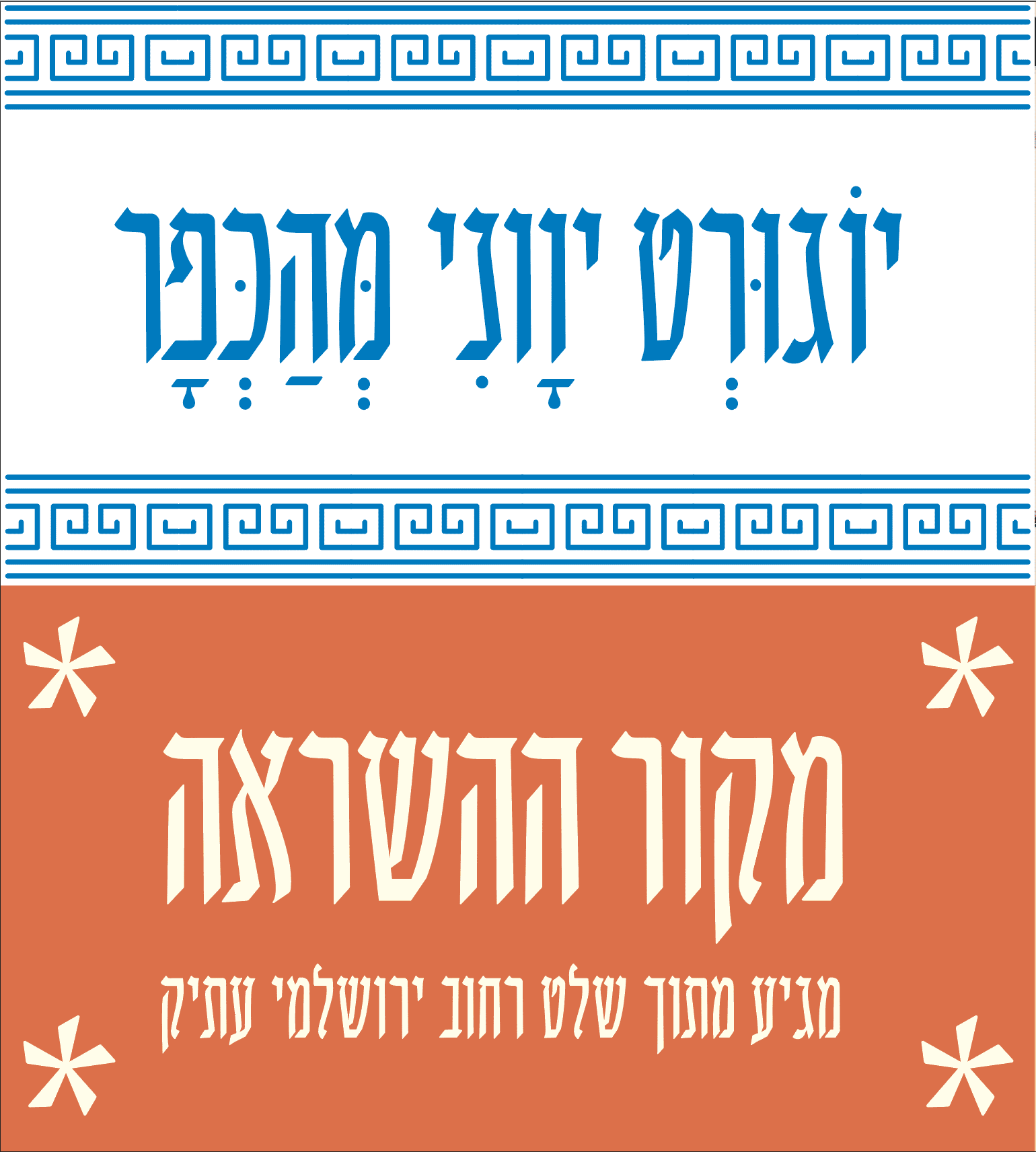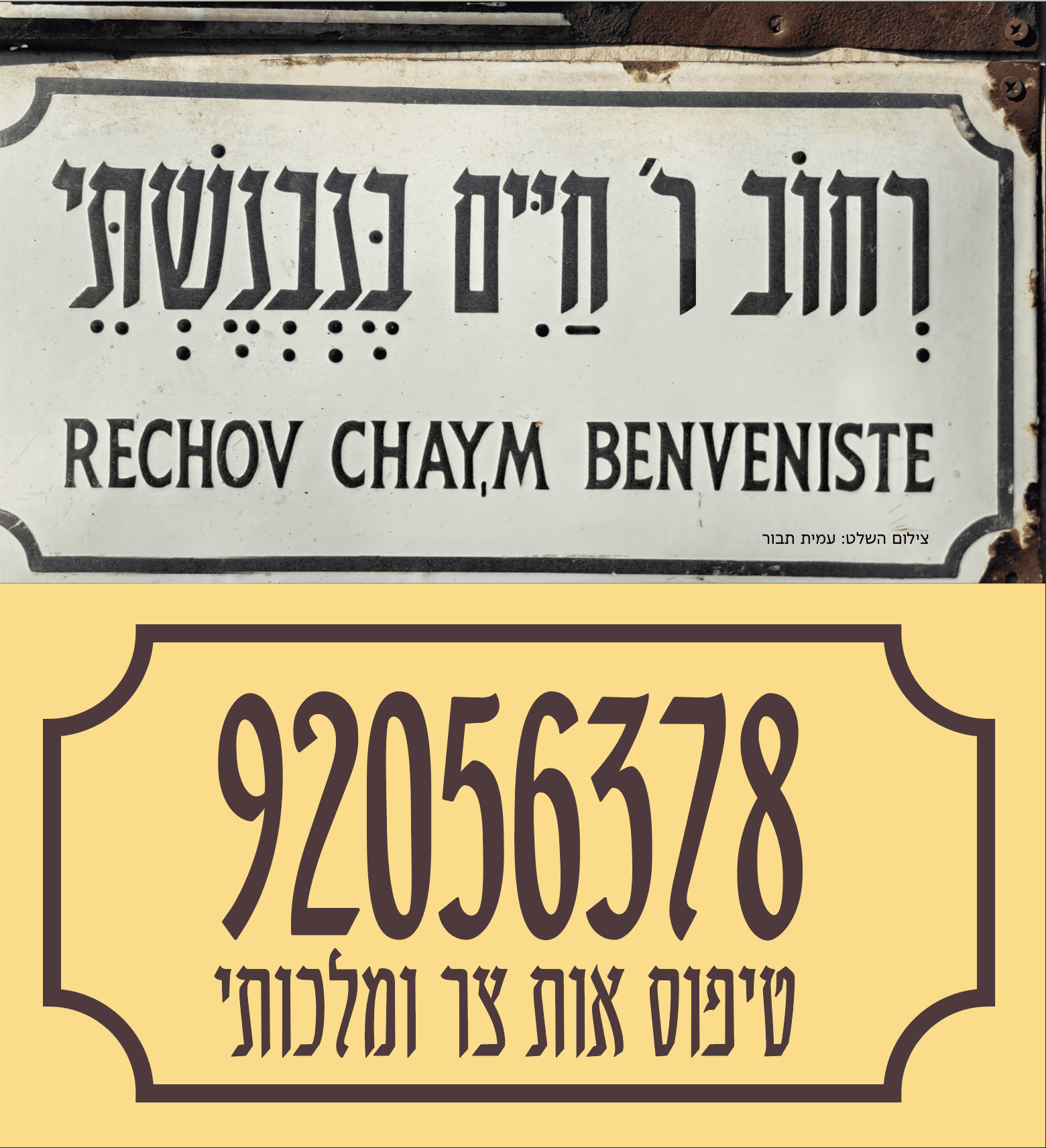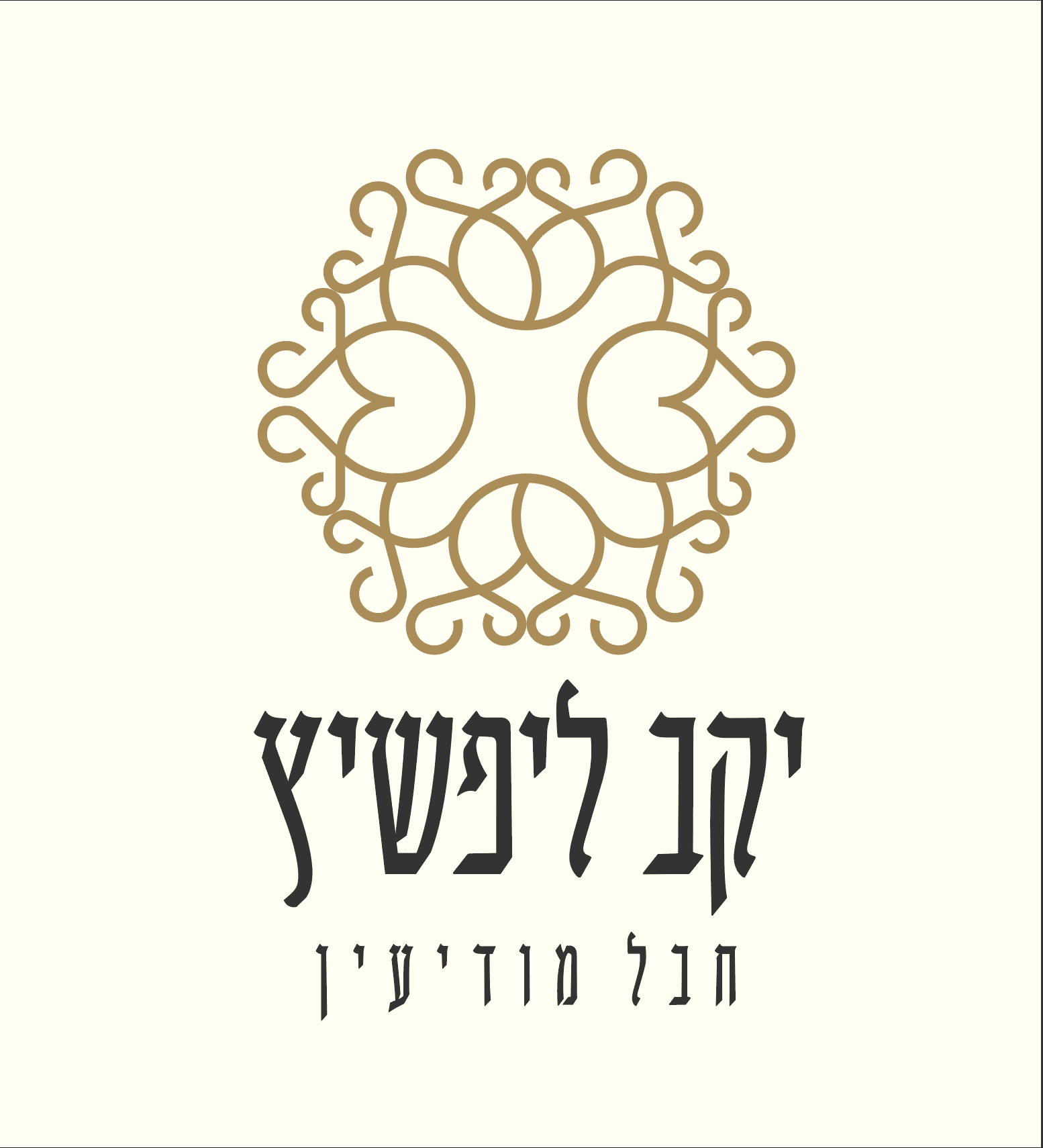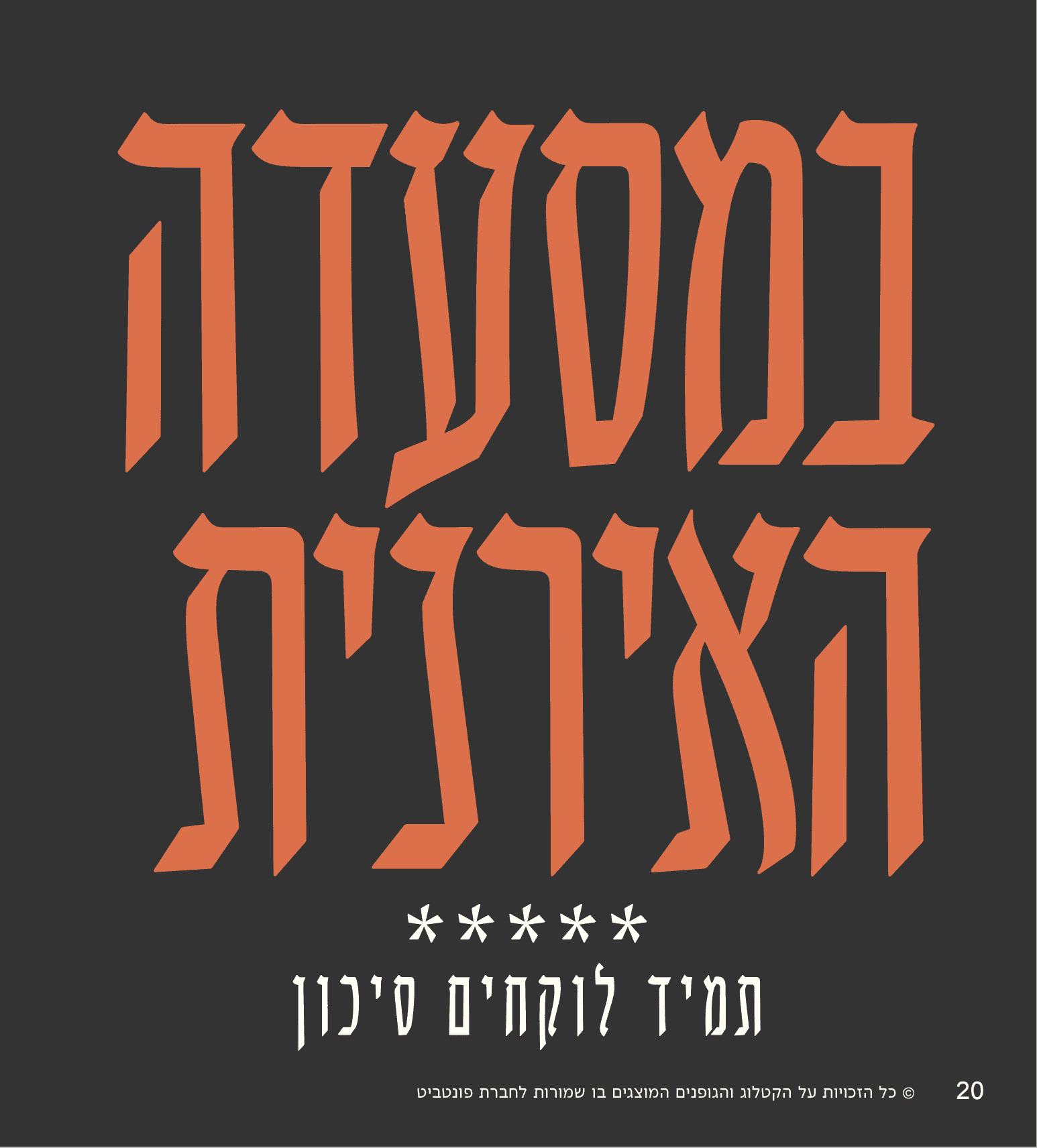
בנבנשתי
שם: Fb Benveniste
כמה מילים על הגופן
נוצר בהשראת כיתוב שהופיע על גבי שילוט עתיק לרחוב בנבנישתי בירושלים. מעניין שלמרות המבנה הצר, שומר בנבנשתי על רמת קריאות מפתיעה, עם ניחוח אצילי, חגיגי ומהודר. זהו גופן שמותח את הגבולות עד הקצה במטרה לשבור את הברקודיות האופיינית לאות עברית צרה שכזו. עיצוב בגופן יעניק מראה אלגנטי. המשדר חלוציות ושורשיות, וגם יהווה פתרון אידיאלי לטקסט רב על שטח מוגבל